今回は「ゲーム実況」配信動画で、人気ある日本語フリーフォントをまとめてみました。
Youtubeで「ゲーム実況」配信動画はとても人気あるコンテンツで、多くのYoutuberが配信しています。そんな「ゲーム実況」配信動画の中でよく利用されている・頻繁に使用されている人気あるおすすめのフリーフォントをご紹介します。
配信するゲーム内容やセリフ内容、配信者のキャラクターにあわせてフォントを選んでみてください!
「ゲーム実況」配信で人気のおすすめフリーフォント
以下のサンプル画像は、「ゲーム実況配信」のサムネイルやテロップで使用したイメージになります。画像内以外のフォントも本記事ではたくさんご紹介しているので、ぜひ見て参考にしてください。
「ゲーム実況」動画で定番のフォントは、フォント名に【定番】と記載をしています。まずどのフォントにしようか迷われている方は【定番】が付いているフォントからダウンロードしてみても良いかもしれません。
【定番】けいふぉんと!
けいふぉんと!は、アニメ『けいおん!』のロゴタイプをヒントに作成したフォントです。一般的なゴシック体より手書きのような躍動感あるフォントなので、ほどよいポップな印象がゲーム配信動画では人気なのかもしれません。
【定番】キルゴU
キルゴUフォントは、ゴツゴツした太めのウェイトでインパクトがあり、元気のある様子が見えるデザインになっているので、実況動画ではとても人気の高いフォントの1つです。
テロップでもよく利用されていますし、ゲーム実況動画のYoutubeのサムネイルデザインでも使用しているのをよく見かけます。
源暎きわみゴ
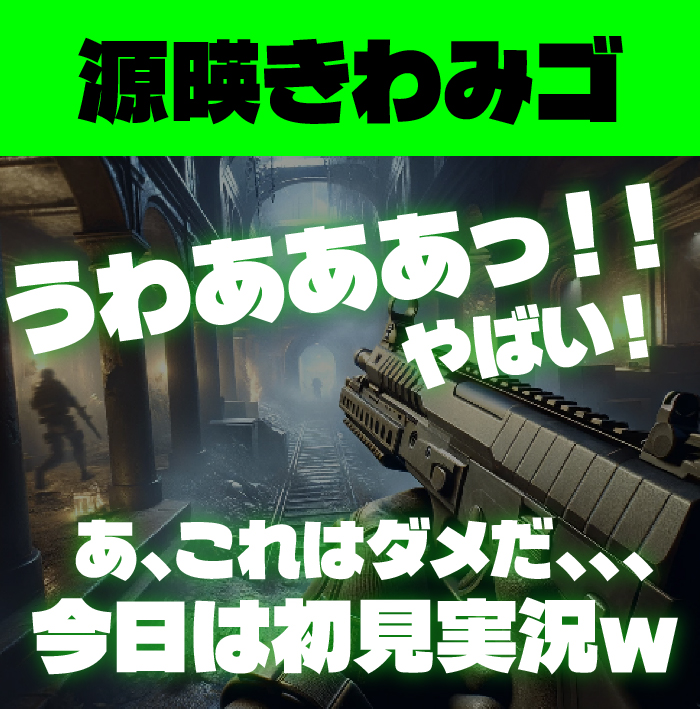
源暎きわみフォントは、超極太フォントで視認性・判読性も高く、強い印象があり、目を引くフォントなので、ゲーム実況系のサムネイルや動画制作にぴったりなフォントです。
【定番】チカラヅヨク
851チカラヅヨクフォントは、ぶっといペンで書いたかのようなペンの字のフォントです。荒々しく、たくましい、印象になるので、ツッコミ系のセリフテロップにぴったりなフォントです。
【定番】チカラヨワク
851チカラヨワクフォントは、弱々しくフニャフニャのフリーフォントです。
弱々しいネガティブなツッコミ系やセリフのテロップにぴったりなフォントです。
【定番】ラノベPOP
ラノベポップフォントは、弾むような楽しい雰囲気をフォントで、マジックペンで書いたような遊びが入っているデザインです。どんな動画にもマッチするフォントなので、とりあえず入れておいて損はないフォントです。
【定番】零ゴシック
零ゴシックフォントは、ガラスのように文字が割れていたり欠けていたり加工が施されているインパクトあるフォントです。
テロップ全てに使うというよりは、印象的なシーンや、インパクトを出したいシーンなどのテロップに使うと効果的です。ゲーム実況動画のサムネイルのデザインなどでぴったりです。
【定番】異世明
異世明フォントは、異世界にワープする際のグニャッとしたイメージをフォントで再現しているフォントです。
こちらのグニャッとした加工が、「ゲーム」ジャンルにぴったりハマります。アクションやファンタジー系のゲーム実況などにぴったりです。
【定番】鉄瓶ゴシック
鉄瓶ゴシックフォントは、、極太のゴツゴツとした質感の味わい深い一風変わったフォントです。
ゴツゴツした質感が、優しい印象や柔らかい印象を作り出しているので、どんなジャンルのゲーム実況動画でもあうフォントとなっています。
デラゴシック
デラゴシックワン(Dela Gothic One)フォントは、超極太フォルムでどっしりとしているインパクトがある平体フォントです。
テロップやサムネイルにインパクトを出すならこのフォントがおすすめです。
暗黒ゾン字
暗黒ゾン字フォントは、ホラー系フォントです。ミステリー系・ホラー系のゲーム実況動画などにぴったりなフォントです。
文字を見ているだけでも恐怖感を煽られますね。
玉ねぎ楷書激
玉ねぎ楷書激フォントは、毛筆で力強く書かれたインパクトある筆フォントです。
動画のテロップで筆文字は合うかな?と思いますが、ゲーム実況だとぴったり合うですよね。サムネイルのデザインなどでも◎
瀞ノグリッチ黒体
瀞ノグリッチ黒体フォントは、グリッチエフェクトの効いたフォントになっています。
グリッチエフェクトの加工が「ゲーム」ジャンルにぴったりハマるので、SFやファンタジー系のゲーム実況などにぴったりです。
たぬゴ
たぬゴフォントは、手書き感の味わいがあるゴシック系フォントです。
柔らかい雰囲気をもつフォントなので「あつ森」のようなほのぼの系のゲーム実況などにぴったり合うフォントです。
源界明朝
源界明朝フォントは、限界ギリギリまでグランジ加工されているフリーフォントです。とてもインパクトがあるので、テロップやサムネイルに向いているフォントです。
ふぉんとは怖い
ふぉんとは怖いフォントは、フニャ〜としているホラー系明朝体フォントです。ミステリー系・ホラー系のゲーム実況動画などにぴったりなフォントです。
恐怖感のあるセリフのテロップなどにピッタリ合うフォントです。
にくまる
にくまるフォントは、ゆるくて、やさしく、柔らかい雰囲気が特徴のデザインフォントです。Youtubeなどの動画制作やテロップなどでも人気のあるフォントです。
チェックポイント
チェックポイントフォントは、独特の極太なウェイトをもちながら、少しポップでユニークに作られているフォントです。
イモケンピ
FZイモケンピフォントは、文字の輪郭がギザギザな加工が施されているユニークなフォントです。ゲーム実況でもよくあるように、強めに強調したい文字・ツッコミ文字などに取り入れると効果的に使うことができるフォントです。
ゴチカクット
851ゴチカクットは、電機文字をイメージされたフォントです。
シュッとしていて、近未来的な雰囲気をもつフォントです。動画をカッコいいイメージに仕上げたいときに取り入れると効果的です。
ベストテン
ベストテンFONTは、懐かしいレトロなゲームを思い出す10×10で作られているドットフォントです。ドットフォントを取り入れると一気にゲーム感が演出できます。